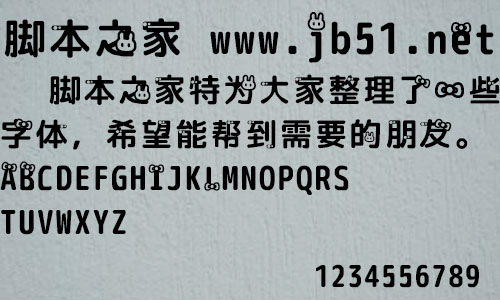
字體管家乖小兔是一款不錯的藝術(shù)字體,由Aa字庫出品,字體筆觸適中,字形端正,以卡通兔子作為點(diǎn)綴,具有很好的視覺感,適合應(yīng)用于藝術(shù)設(shè)計(jì)、平面宣傳設(shè)計(jì)、網(wǎng)頁設(shè)計(jì),書法字帖等領(lǐng)域,需要的朋友可以前來本站下載。